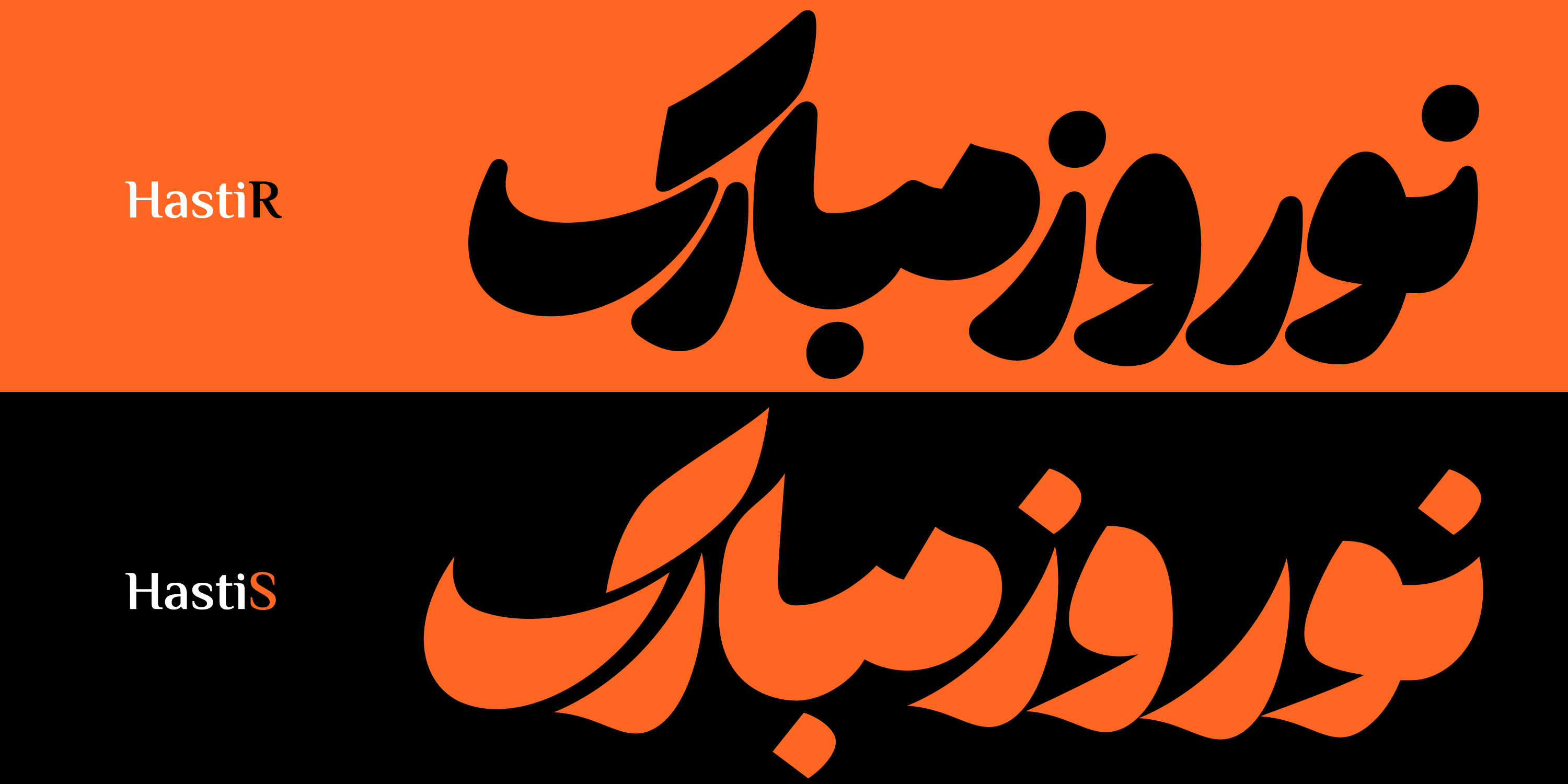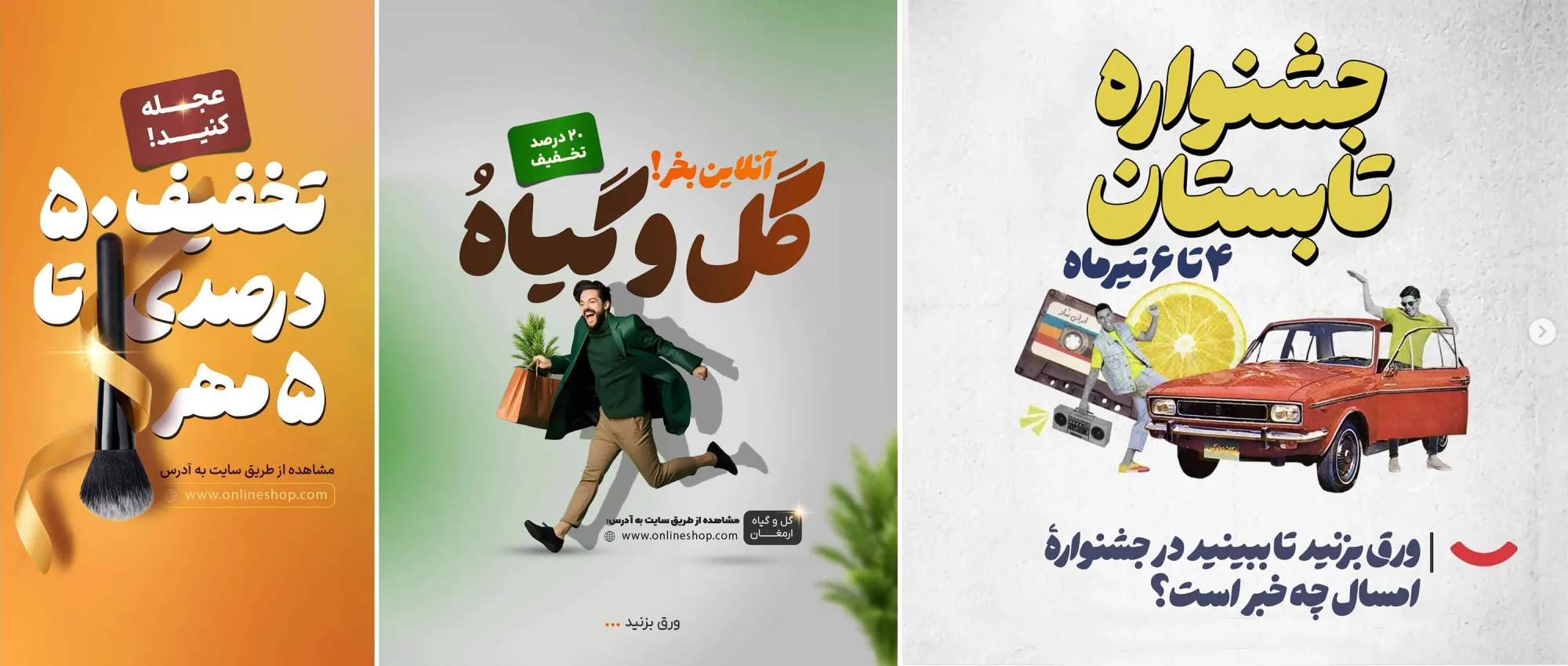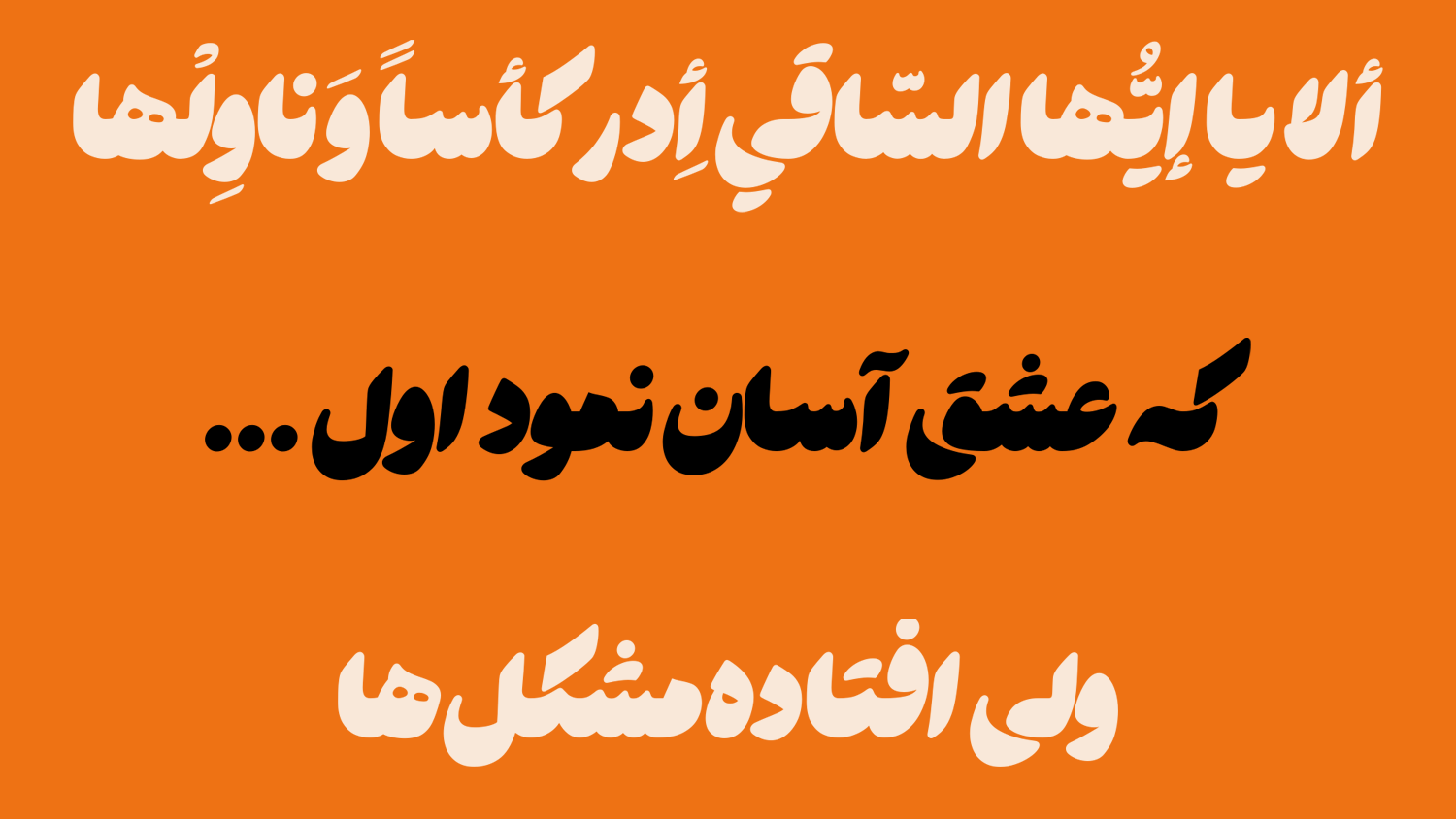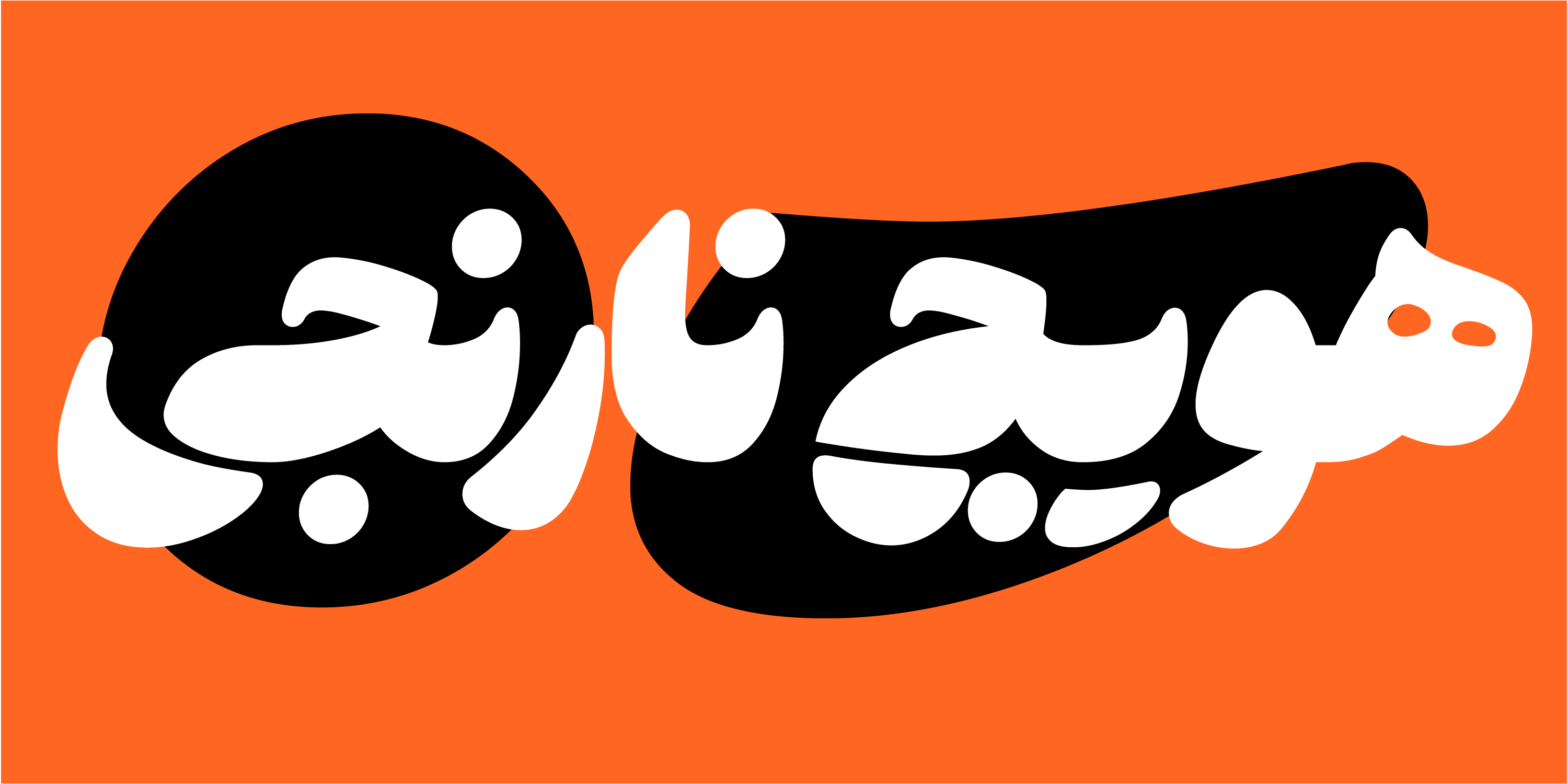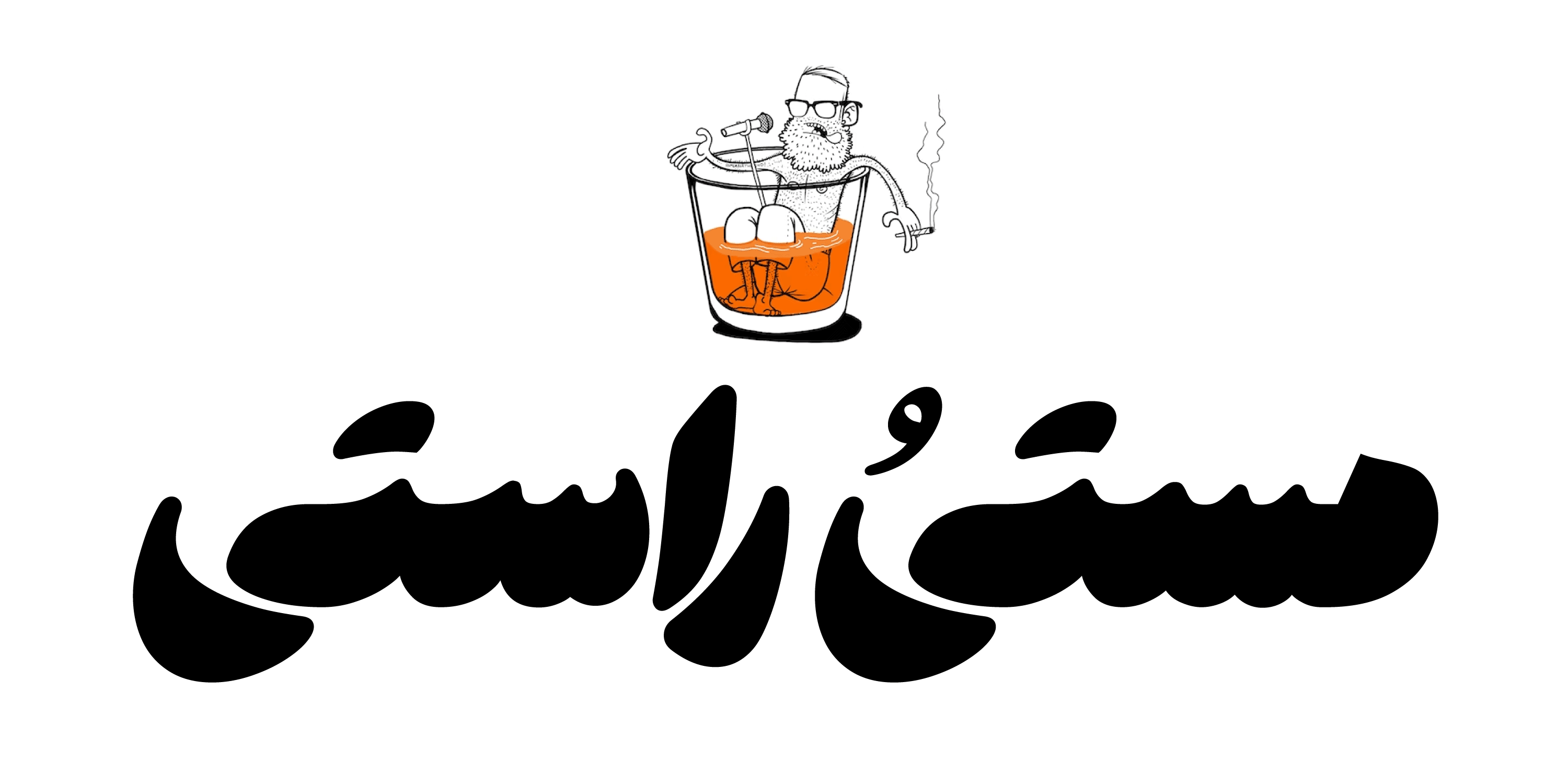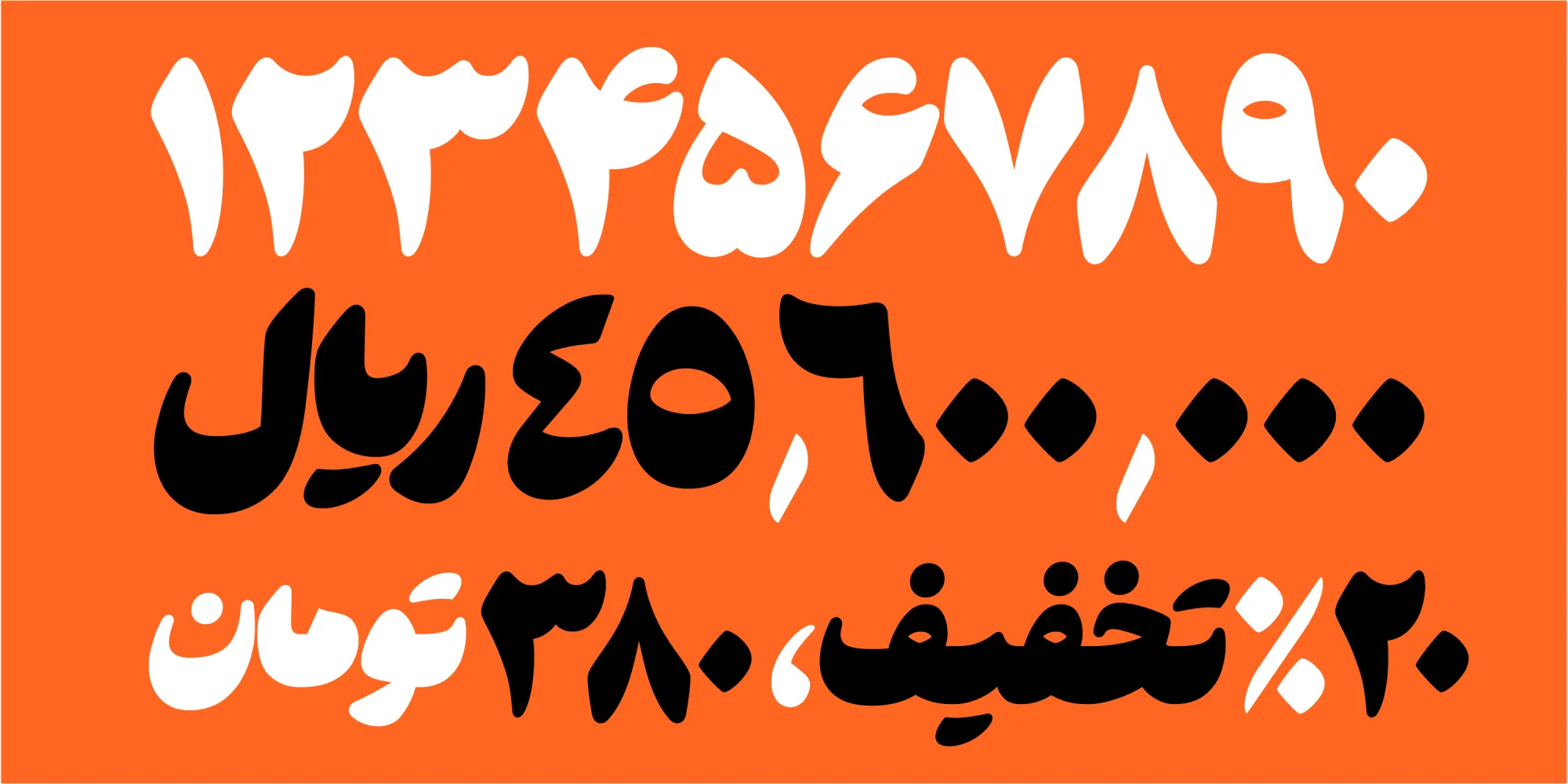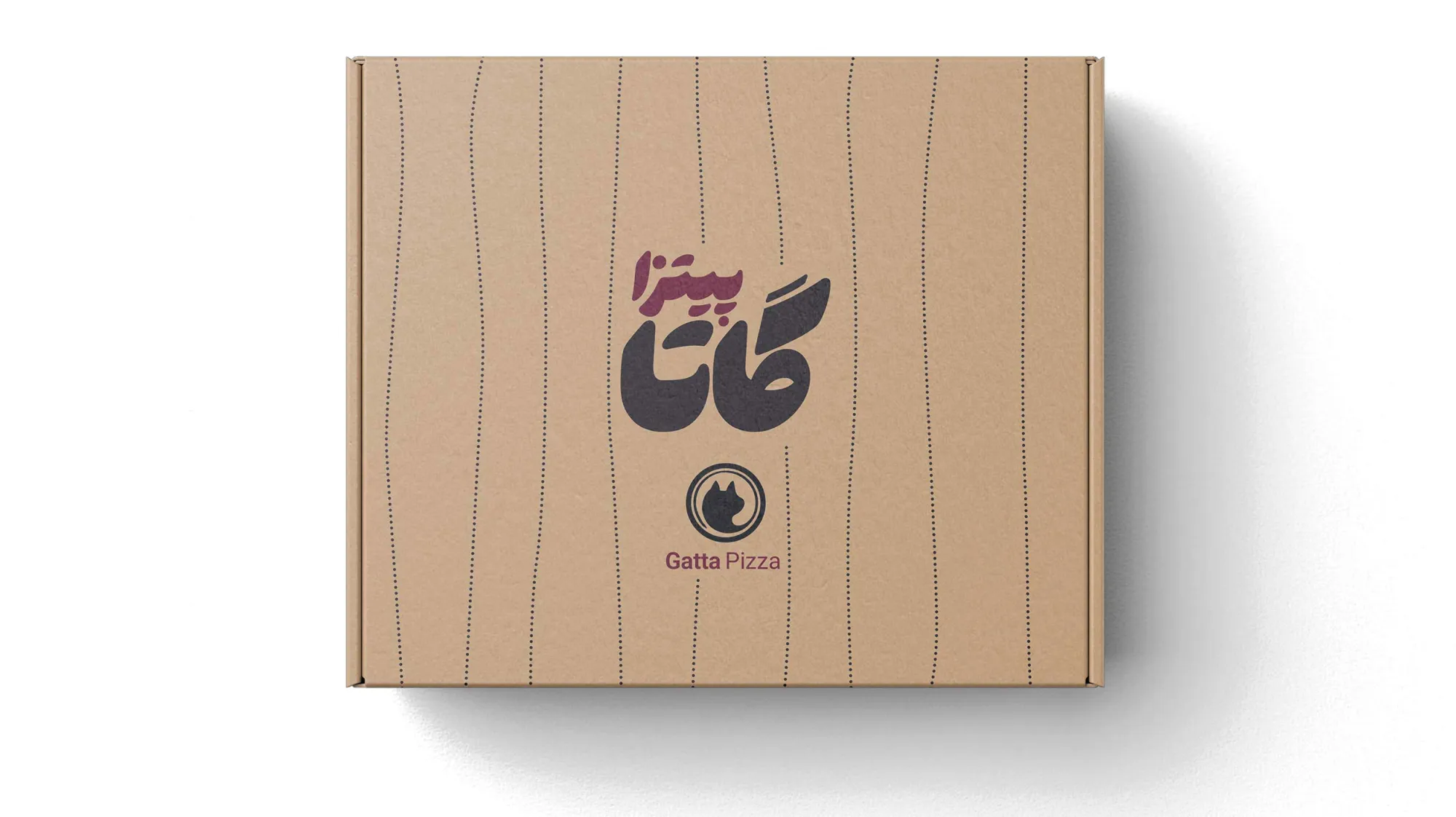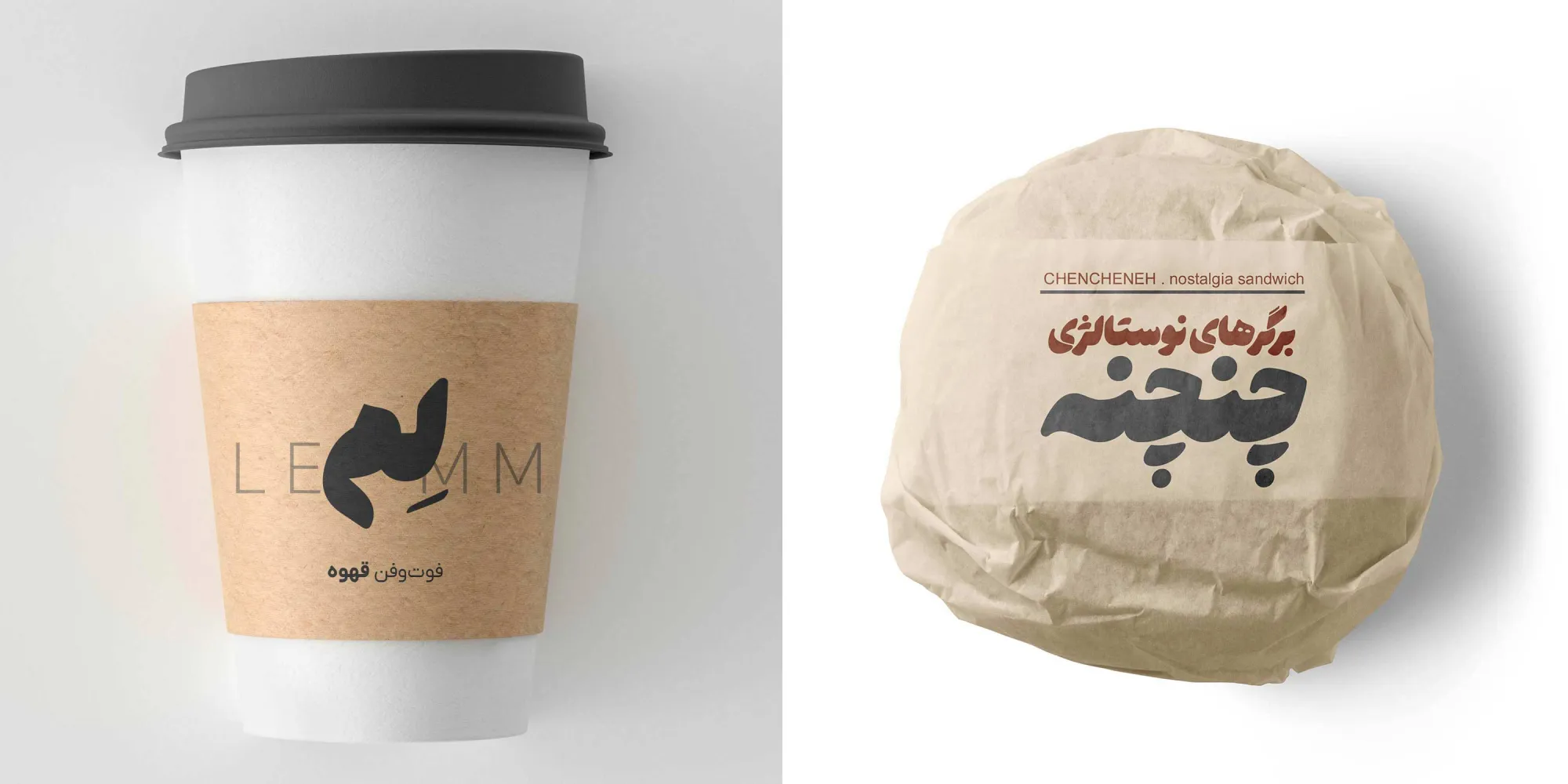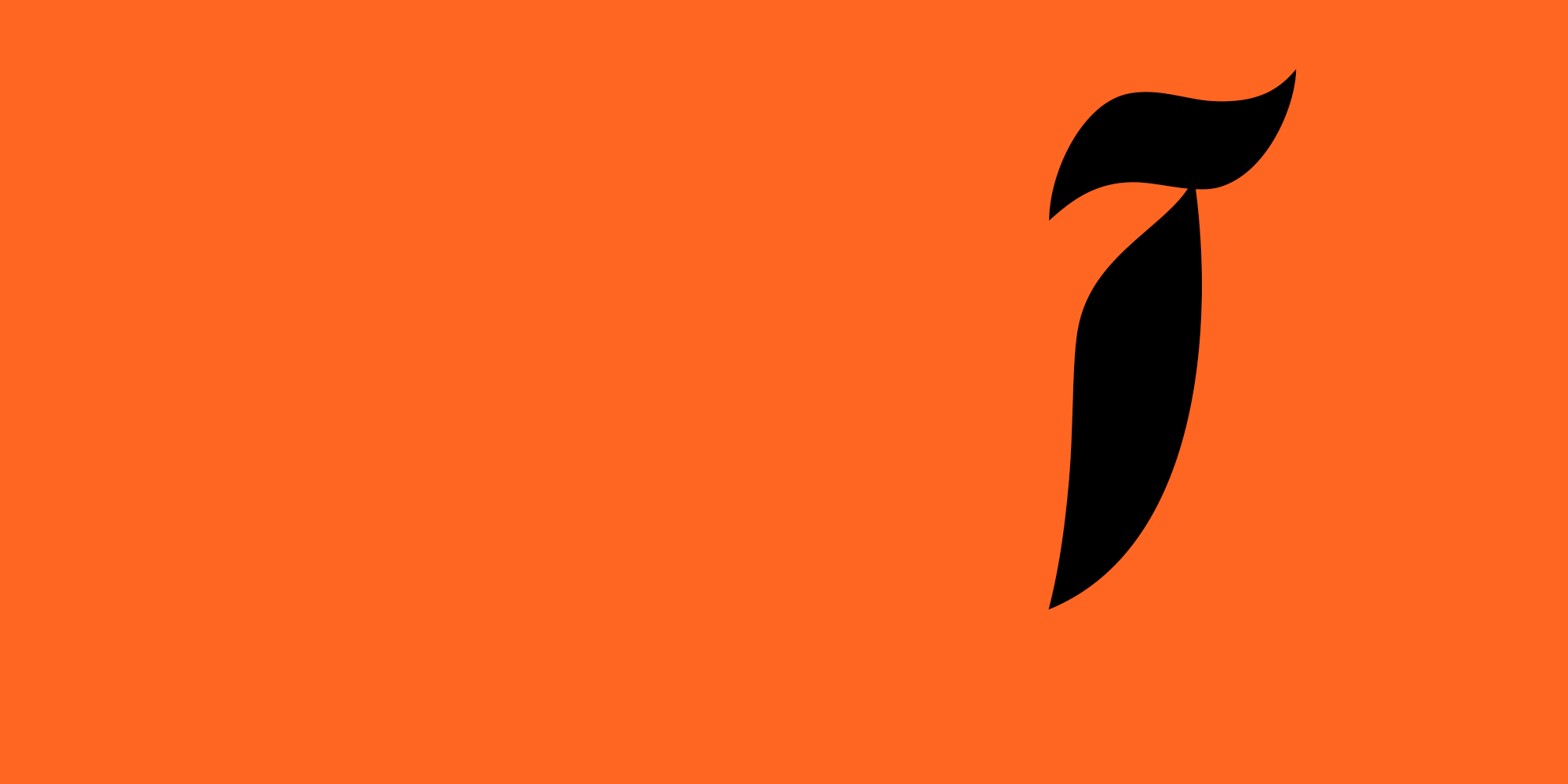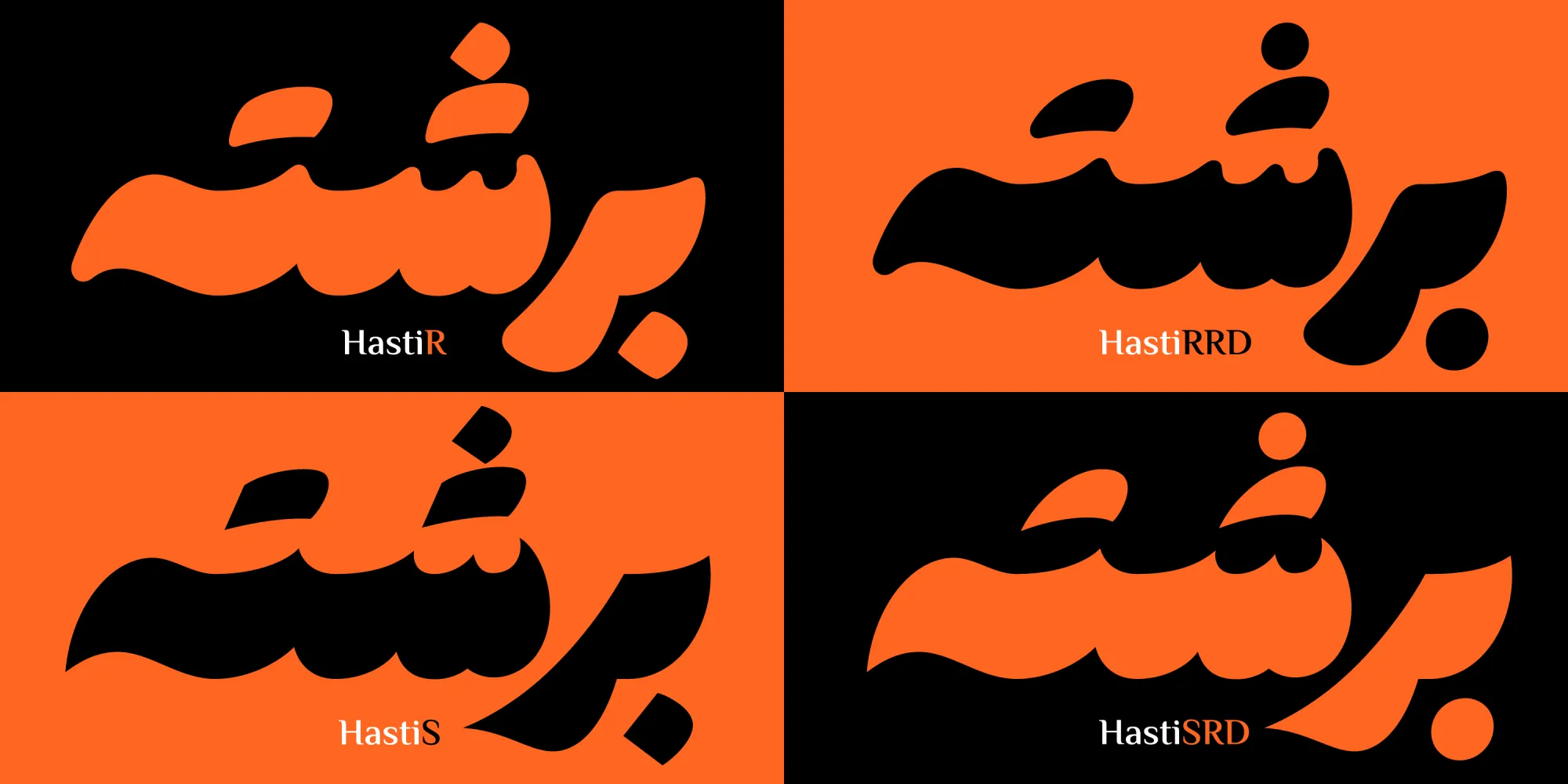
فونت هستی (Hasti)
نام هستی
نام نمایشی Hasti
طراح مسلم ابراهیمی
فونت هستی (به انگلیسی: Hasti) یک فونت جدید برگرفته از خط نستعلیق بازاری است که با ایجاد تغییراتی از نظر فشردگی، افزایش وزن و همچنین خطوط استنسیل رشد و پرورش داده شده تا در نهایت به این فونت زیبایی که می‌بینیم تبدیل شود. این قلم با توجه به ظاهر و ساختاری که دارد، مناسب عناوین، کارهای گرافیکی تبلیغاتی و نمایشی است. فونت هستی رایگان نیست و با توجه ه طراحی که از نظر وزن، دو استایل متفاوت و امکانات برای حروف جایگزین دارد، در یک بسته قابل خریداری است.
مسلم ابراهیمی طراحی این فونت جدید را پس از ۳ سال وقفه در زمینه طراحی تایپ ساخته است که حال برای استفاده عمومی در دسترس قرار گرفته است. تغییراتی که روی این فونت اعمال شده تا حدودی آن را به سبک فانتزی و دست‌نویس (صرفا از نظر سبک نقطه گذاری) تبدیل کرده است. اما اساسا این فونت همان ویژگی‌های نستعلیق را در دل خود دارد؛ با اینکه اصلا فونت خوشنویسی نیست.
در ادامه این نوشته از سایت فونتچی به نقد و بررسی کامل فونت هستی خواهیم پرداخت. قلمی که با توجه به الهام گرفتن از خط نستعلیق فشرده، می‌تواند برای کارهای گرافیکی صورت گرفته و بدون نیاز به انجام کارهای گرافیکی و افکت پیچیده کار شما را برای طراحی پوستر، بنر و کارهای خلاقانه از نظر راحت کند.
قلم هستی با فونت زیبا به سبک خوشنویسی نستعلیق بازاری طراحی شده که در دیوار نویسی و تبلیغات شهری با قلم درشت، خطاطی می‌شوند. اما به منظور تبدیل این قلم به یک فونت هنری، سبک بولد و فشرده روی آن اعمال شده است. چرا که نستعلیق به تنهایی ظرافت لازم را برای تبدیل شدن به یک فونت هنری ندارد.
به همین دلیل چشمی حروف در کمترین میزان از نظر اندازه قرار گرفته‌اند تا فونت را بیشتر از پیش ضخیم‌تر و نمایشی‌تر نشان دهند. همچنین شکل برخی حروف «ک، ی، ح» به منظور فشردگی بیشتر، شکسته و منقطع شده است. ساختار کلی قلم با توجه به وضعیتی که از نظر ضخامت دارد، یک فونت سیاه به نظر می‌رسد با اینکه تا حدودی خاکستری بودن را هم القا می‌کند.
سبک طراحی و وزن فونت هستی
فونت هستی بر اساس خط نستعلیق بازاری طراحی شده که کاملا خوشنویسی‌طور به نظر می‌رسد. این فونت با ایجاد تغییراتی بر روی تمامی بخش‌های حروف، با یک سبک جدید نستعلیق فشرده ساخته شده که اثری از ترکیبات و اتصالات نستعلیق نیست اما شکل حروف تا حد امکان شبیه نستعلیق است.
در طراحی این فونت اندازه حروف در بخش‌های مختلف افقی و عمودی به شیوه معاصر امروزی در نظر گرفته شده است. منحنی‌ها ظاهری کاملا نرم دارند، طره‌ها با گوشه گرد هستند و ضخامت حروف نیز یکسان نیست. تا حدودی مانند فونت دانا هم یک استایل ایتالیک برای حروف درنظر گرفته شده است.
به منظور نمایشی‌تر کردن فونت hasti، از سبک خطوط استنسیل نیز استفاده شده است که برش‌هایی خطی در زوایای مختلف برای تمام حروف درنظر گرفته شده است. البته این برش‌ها، در مکان‌های خاصی از حروف تعبیه شده تا ظاهر آنها را نمایشی‌تر کنند.
در نسخه اولیه هستی شاهد یک سبک طراحی بودیم که منحنی‌ها و انتهای حروف دارای ظاهری گرد و نرم هستند. اما در نسخه دوم سبک جدیدی به صورت نوک تیز به آن افزوده شده است که حالا شاهد دو سبک «گرد و تیز» با نام Hasti Rounded همراه با سبک «نقطه کلاسیک و گرد» با نام Hasti SRD هستیم.
پشتیبانی از چند زبان متنوع
ویژگی ظاهری قلم طوری است که گویی اسم هستی با فونت فارسی درهم تنیده شده؛ از چند زبان مختلف پشتیبانی می‌کند که در وهله‌ی اول زبان فارسی است. تمامی حروف و گلیف‌های فارسی این قلم برگرفته از خط خوشنویسی فشرده و اعمال وزنی فشرده‌تر طوری طراحی شده‌اند که اعراب و سایر کاراکترها در هم‌نشینی خوبی با هم قرار گیرند.
در سایر زبان‌های مبتنی بر رسم خط فارسی همچون زبان عربی، کردی و اردو نیز این مسئله رعایت شده است. به‌طوری که گلیف‌های هر زبان از نظر تفاوت در برخی حروف، مانند حروف «ك، ي، ة، ؤ، ئ» در زبان عربی یا «ﮧ، ﮩ، ے» در زبان اردو، بر اساس استاندارد بین المللی یونیکد طراحی شده و هر کدام گلیف اختصاصی خود را بر اساس یونیکد دارند.
اعراب و کاراکترهای تزئینی در زبان‌های کردی و اردو زمانی که در کنار سایر کاراکترهای «سکون، تشدید، همزه» قرار گیرند هم‌نشینی خود را حفظ خواهند کرد تا ساختار خوشنویسی و نمایشی بودن فونت به هم نریزد. همانطور هم که انتظار می‌رود، اعراب در این قلم بر خلاف حروف وزن کمتری دارند.
در آپدیت فونت هستی ۲ نیز برخی ترکیبات عمدا تغییر داده شده تا بر خلاف ظاهر رایج خود، با قرارگیری در کنار هم با ظاهر متفاوتی تایپ شوند. از این‌رو هم فونت نمایشی‌تر خواهد شد و هم در ترکیبات این‌چنین، شاهد تفاوت ظاهری چند حرف نسبت به سایر حروف نخواهیم بود.
در فونت انگلیسی هستی از طراحی اختصاصی حروف استفاده نشده و در مقابل از فونت Shrikhand برای حروف لاتین در نظر گرفته شده که ساختاری نزدیک به سبط طراحی فارسی این قلم دارد. اما مشکلی که وجود دارد از نظر فاصله‌گذاری واژه‌ها و کلمات است که انتظار می‌رود در نسخه بعدی بازبینی روی آن صورت گیرد.
دارای ترکیبات و حروف جایگزین متعدد
ویژگی دیگر فونت رایگان هستی، پشتیبانی از ترکیبات و حروف جایگزین متعدد است. با استفاده از حروف جایگزین فونت هستی می‌توانید کلمات را در چند حالت مختلف استفاده کنید. از آنجایی که این فونت مناسب عناوین برای تبلیغات و کارهای گرافیکی خلاقانه بیشتر مورد استفاده قرار خواهد گرفت، چنین ویژگی به شما کمک می‌کند که بدون نیاز به انجام کارهای گرافیکی پیچیده بتوانید چنین تغییراتی را اعمال کنید.